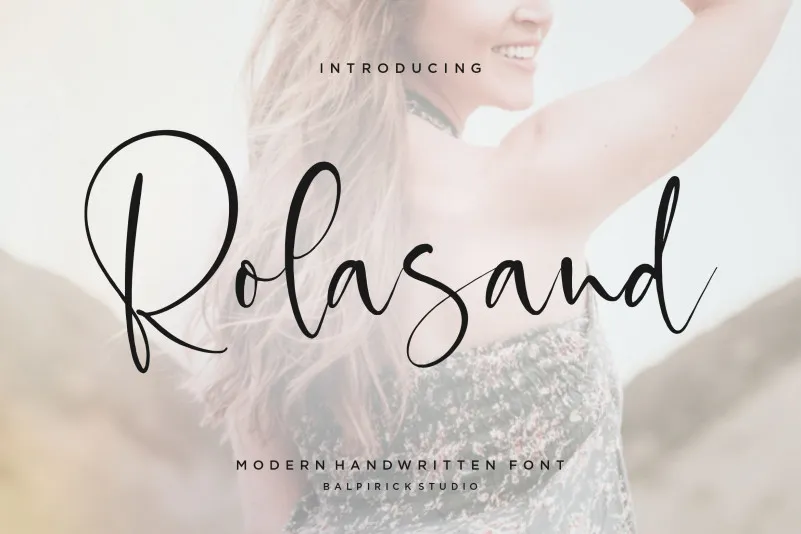
Rolasand Font – Download Grátis
A Rolasand é uma elegante fónta minada, perfeita para adicionar um toque autêntico a seu trabalho de arte digital. Seja para criar embalagens de produtos modernas e envolventes ou para adicionar uma personalidade única aos projetos de marca, esta fonte escrita à mão traz um toque natural que se destaca em qualquer aplicação visual. Ideal tanto para revistas e mídias sociais quanto para destacar textos importantes em casamentos, a Rolasand oferece o charme suave e despojado do texto minado. Este é um recurso gráfico ideal para designers buscam um toque único que se destaca de outras fontes digitais. Sua simplicidade e elegância tornam-a uma ótima opção para expressar mensagens com profundidade, seja em sua marca pessoal ou em qualquer outro projeto visual.